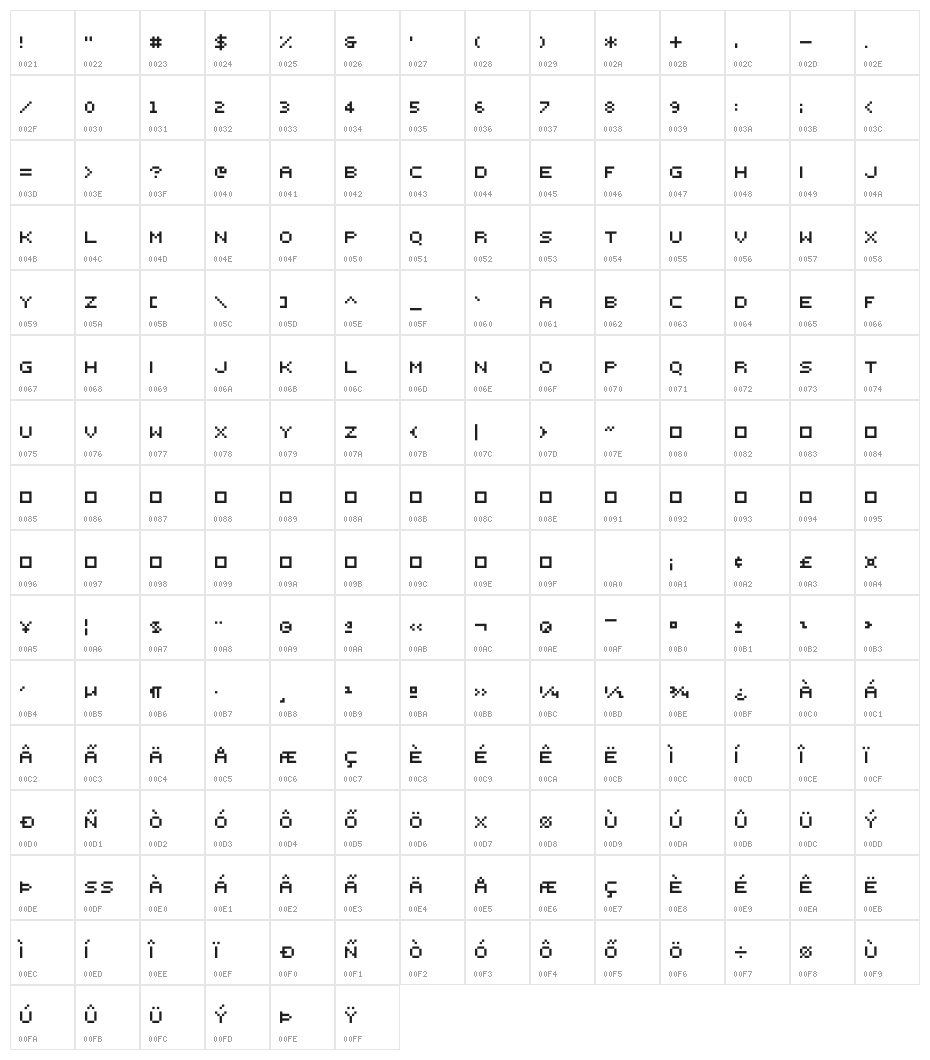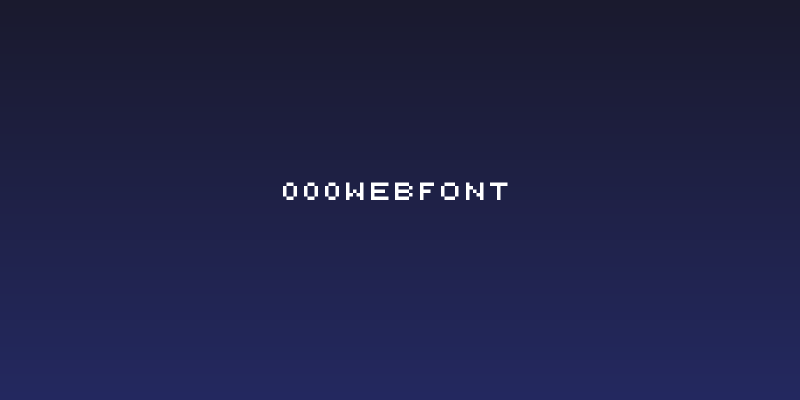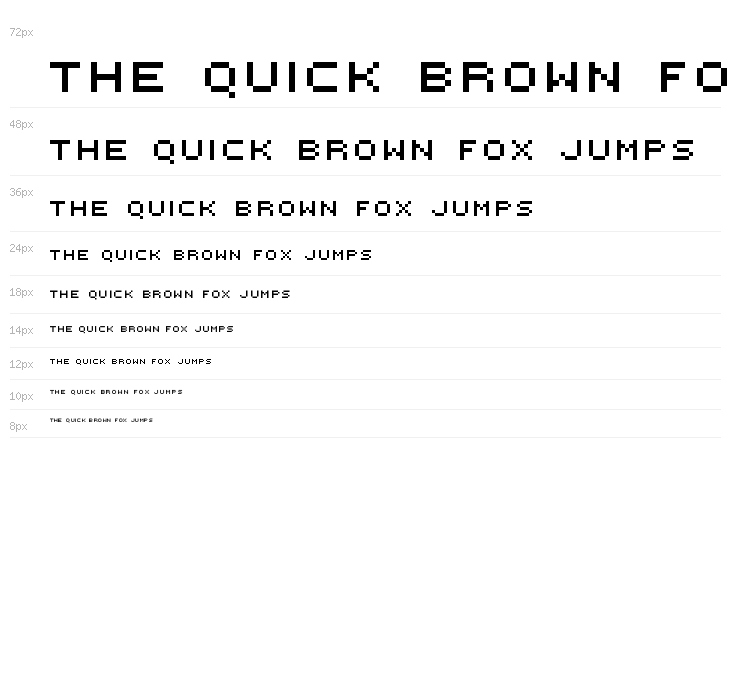
000webfont Font
✎ Pixel
memesbruh03 - Aaron D. Chand
000WEBFONT Groß
000WEBFONT Kleinbuchstaben
000WEBFONT Anderer Schreiben
| Kategorien | Pixel |
| Gesamtstil | Retro, Digital |
| Vorgeschlagene Projekte | Ideal for retro video game designs, digital art projects, tech-themed posters, and any creative work that requires a nostalgic digital look. |